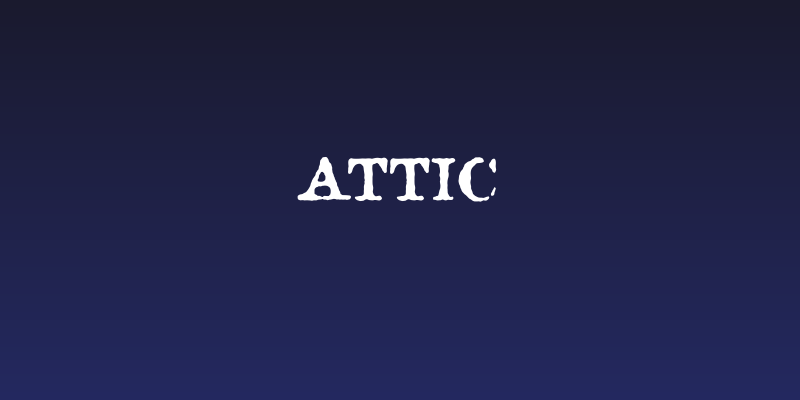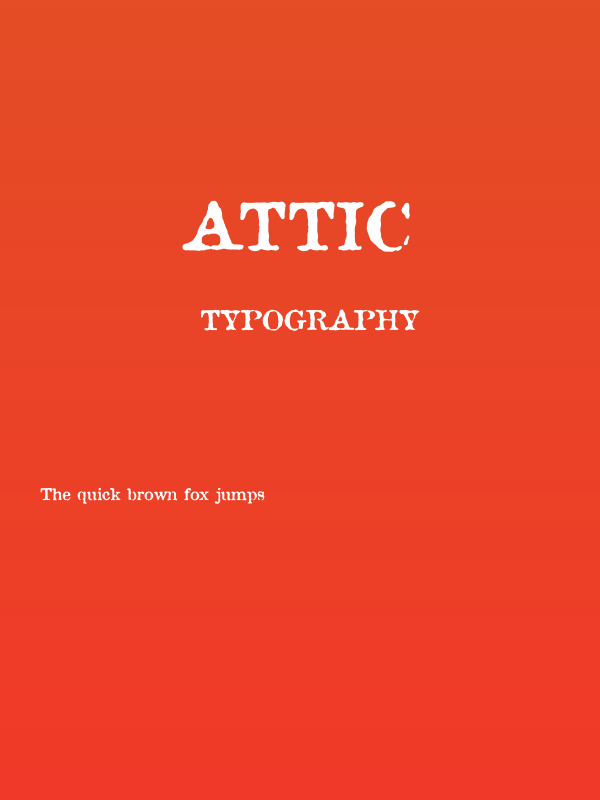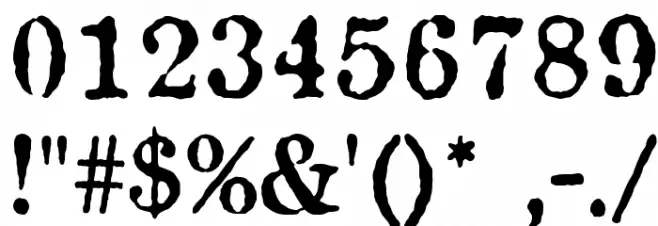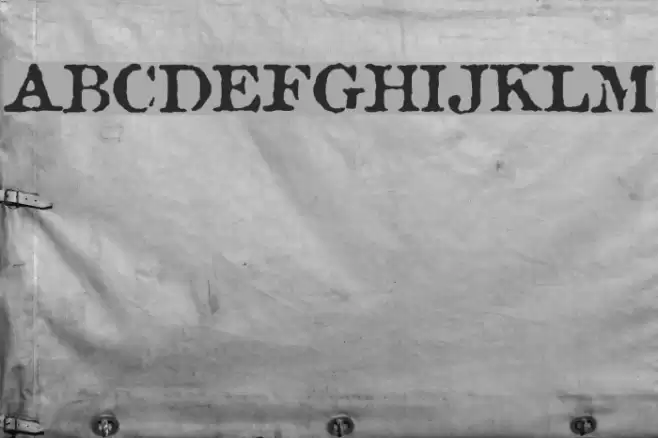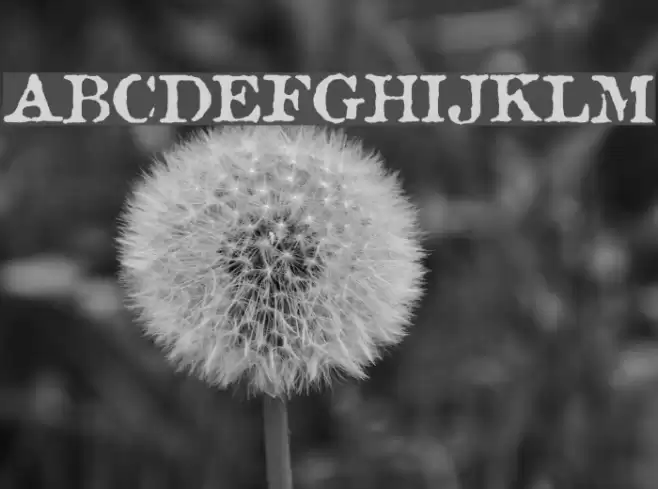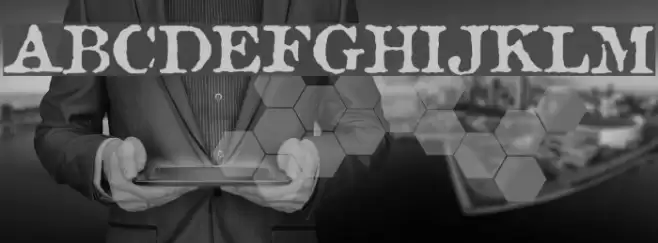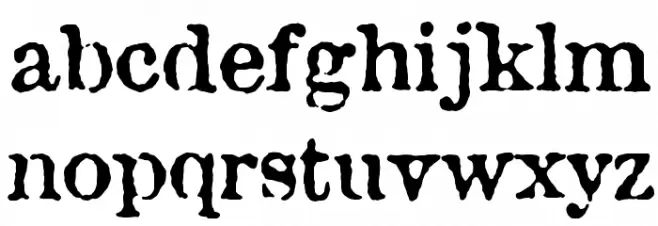
Attic Font
| Общий стиль | Vintage |
| Область применения | Logos, Headlines, Posters |
| Рекомендуемые проекты | Ideal for vintage-themed posters, logos, book covers, and branding that seeks a rustic or historical touch. |